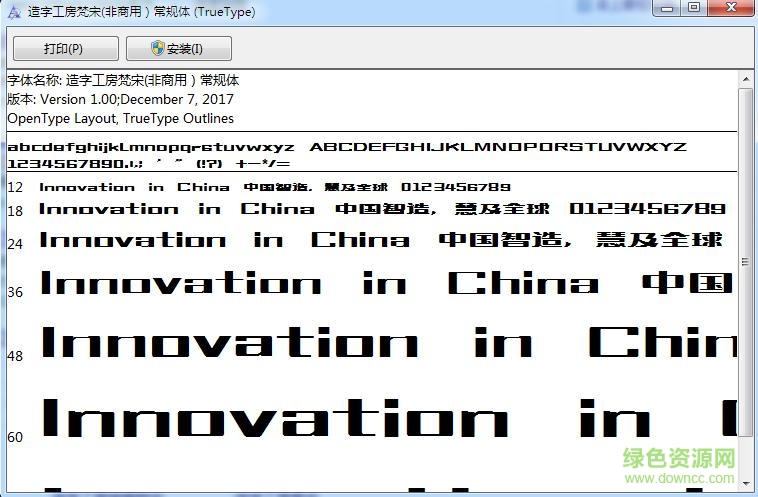
造字工房梵宋
造字工房梵宋字體是一款字形獨(dú)具魅力的電腦中文字體,字體筆畫較粗,并且非常醒目,字形整體看上去比較扁平,適合用來進(jìn)行藝術(shù)的創(chuàng)作,有需要?dú)g迎下載使用!
造字工房梵宋字體簡介
造字工房梵宋是一款將梵文字形與宋體字體完美結(jié)合的藝術(shù)字體,字形扁平有特色,且造型秀美適意、剛?cè)岵?jì),蘊(yùn)傳統(tǒng)宋體風(fēng)格特性!